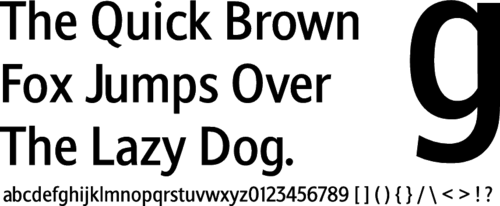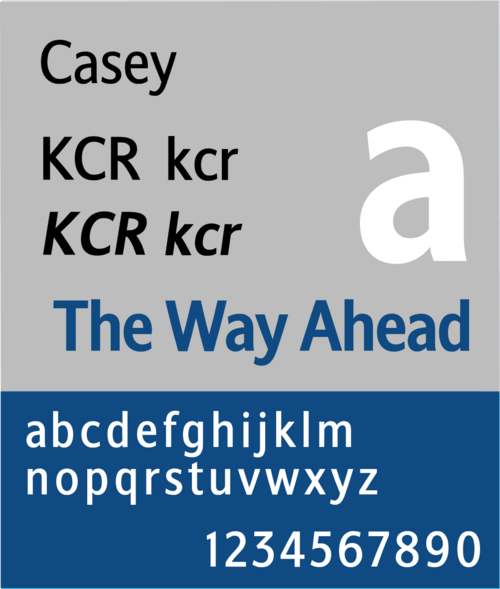
| カテゴリ | サンセリフ |
| 分類 | ヒューマニスト |
| 委託先 | 九広鉄道公司 |
| 鋳造所 | ダルトン・マグ |
| 作成日 | 1996 |
| 別名 | ケイシー(KCRC版) |
Stroudley は、香港の交通事業者である九広鉄道(KCRC)の依頼を受けて、鉄道システムの企業アイデンティティに使用するために1996 年にDalton Maagによって作成されたサンセリフ書体です。鉄道会社が使用したバージョンはCaseyと名付けられました。
歴史
Casey は 1996 年に KCRC によって導入されました。これは、幅広のFrutigerやMyriad (文字)に似た、凝縮されたヒューマニスト サンセリフ体で、Casey という名前は KCRC の最初の 2 文字である KC に由来しています。
ダルトン・マーグは後にケイシーを改良し、「ストラウドリー」という名の商用フォントとしてリリースした。[1]ストラウドリーはその後、ロンドンのセント・パンクラス駅の標識用に作られたバーロウ書体のテンプレートとして使用された。[2]
使用法
ケイシーは、KCRC から鉄道システムでの企業アイデンティティの使用を委託されました。最初に使用されたのは、1996 年に改訂された KCRC のロゴでした。KCRイースト レール (現在のイースト レール ライン) のメトロ キャメル EMU が近代化されたとき、その車両番号がケイシーに明確に表示されました。新しいSP1900列車が運行を開始した ときも、同じことが行われました。
KCR西鉄(馬鞍山鉄道との合併により現在は屯馬線)が運行を開始すると、その使用はWR駅のすべての標識と駅名板に拡大し、公司が配布するチラシやパンフレットにも使用されるフォントになりました。
旧 KCR の標識のほとんどは、鉄道合併後にMTRスタイル ( Myriad書体を使用)に合わせて置き換えられましたが、特定の標識では今でも Casey が見られます。
このフォントは2019年にシンガポールの公共交通機関で使用され始めました。キャンベラMRT駅とトムソン・イーストコーストMRT線の開業時に初めて導入され、以前のフォントであるオーシャンサンズに取って代わりました。このフォントは、コロナ禍以降、チャンギ空港でも使用され始めており、セキュリティ検査の看板、入国審査/免税店の看板、搭乗ゲートの看板などに使用されています。